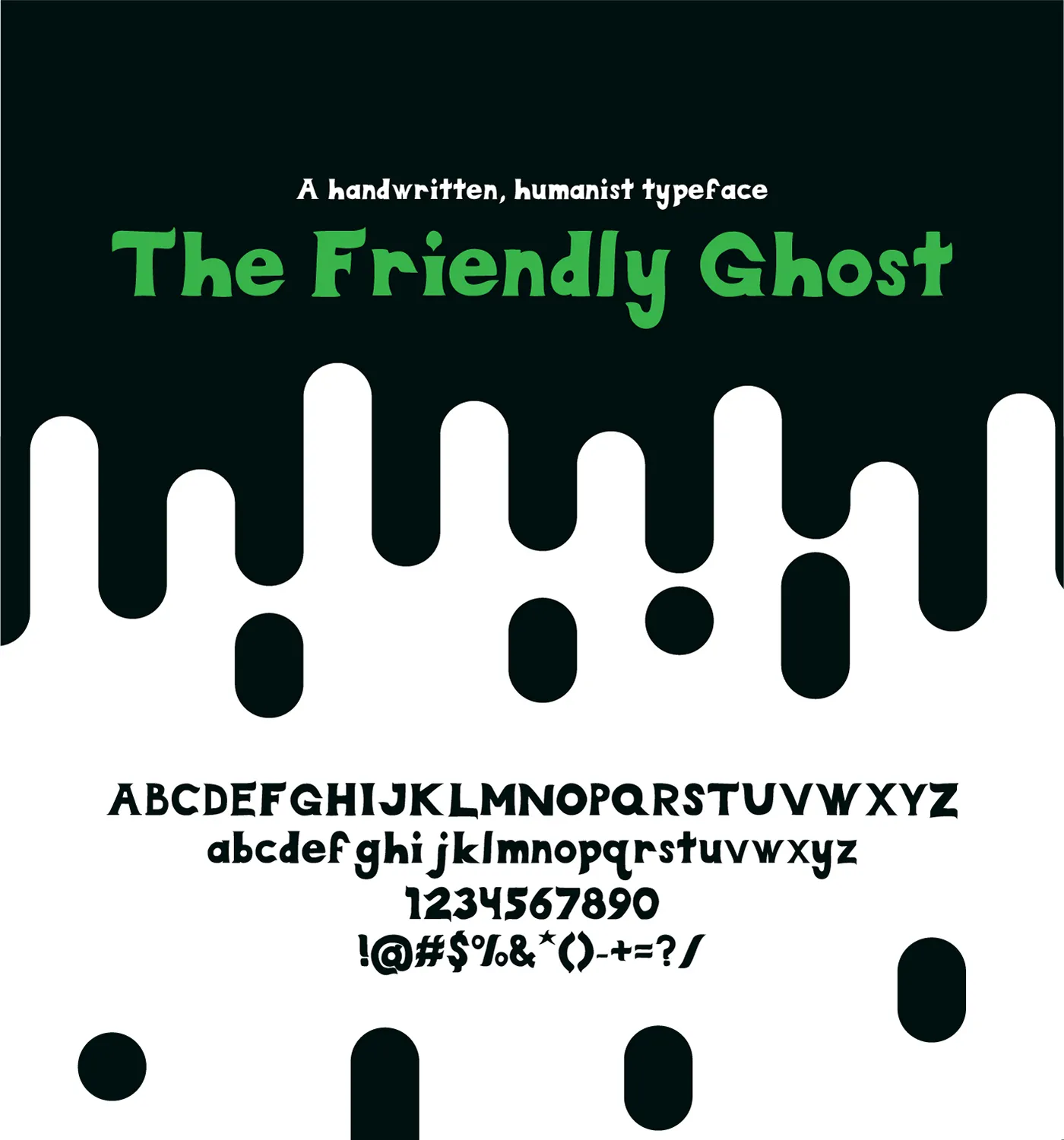
The Friendly Ghost Font
Descubra agora a Fonte Amigável Fantasma! Introduzimos gratuitamente uma nova opção para os amantes do design tipográfico – The Friendly Ghost Font, criado pelo designer Hamilton de Frontenac, Kansas, nos Estados Unidos. Esta fonte foi feita com cuidado e arte, especialmente para aqueles que apreciam mistério, lendas e histórias sobrenaturais. Perfeita para projetos envolventes e cheios de tensão, The Friendly Ghost Font captura exatamente o espírito sinistro e a atmosfera aterrorizante que você busca. Seja para criar letras em um livro sobre mitos do folclore local ou para adicionar uma dose extra de horror à sua próxima publicação online – The Friendly Ghost Font é perfeito para você. Essa fonte serif, criada pelo designer Hamilton, é ideal tanto para aquelas pessoas que desejam um design mais sofisticado e elegante quanto para quem busca uma atmosfera mais sombria e misteriosa. Experimente incorporar a The Friendly Ghost Font em seus próximos projetos gráficos – ele certamente dará um toque único ao seu trabalho.